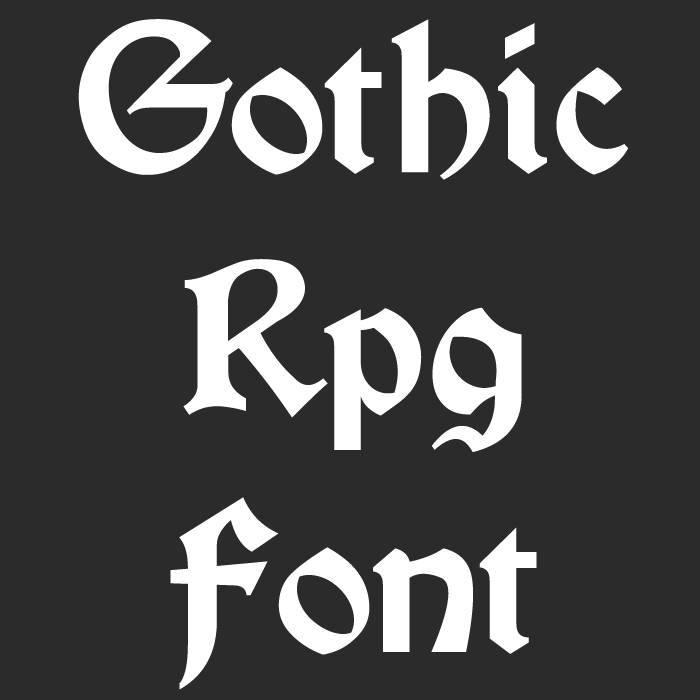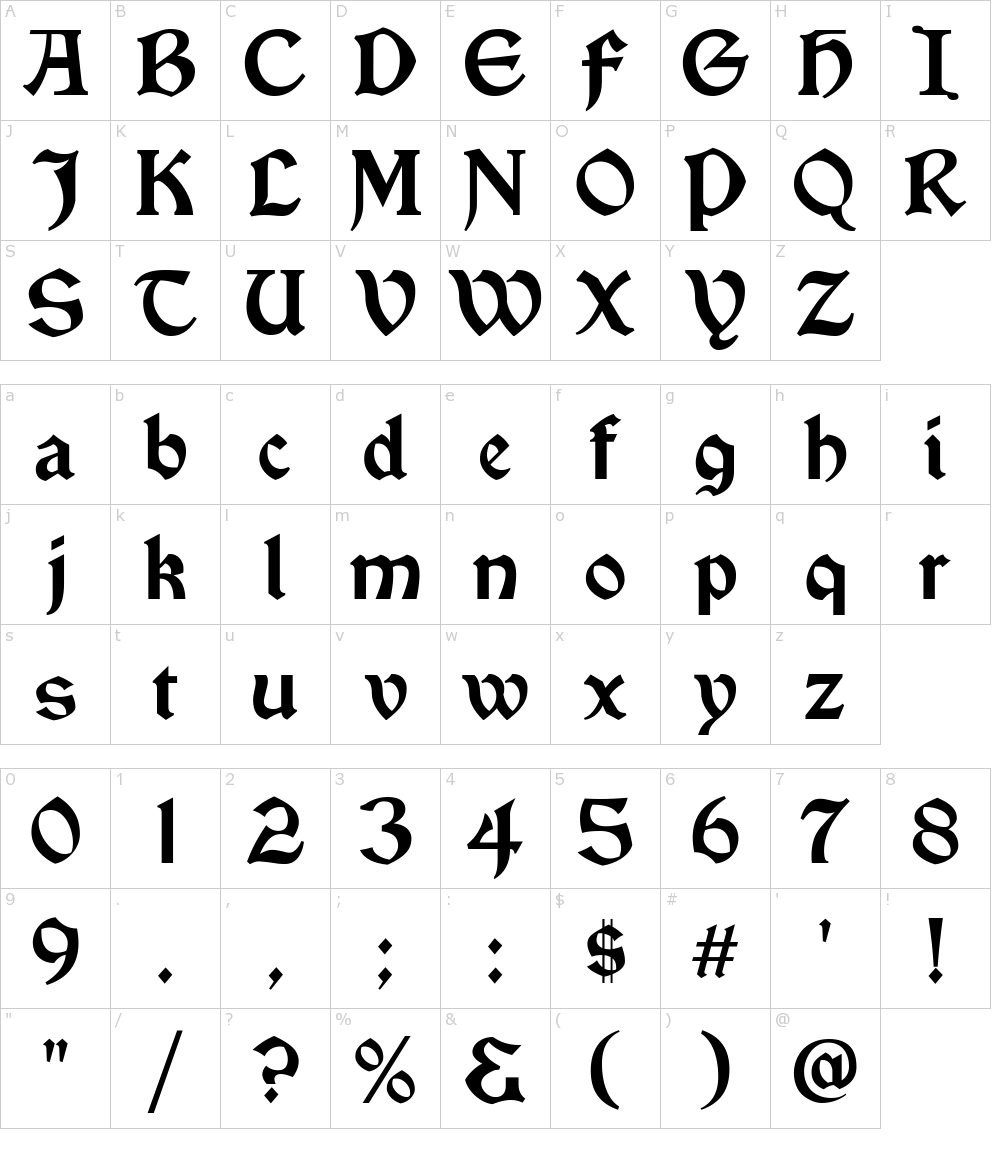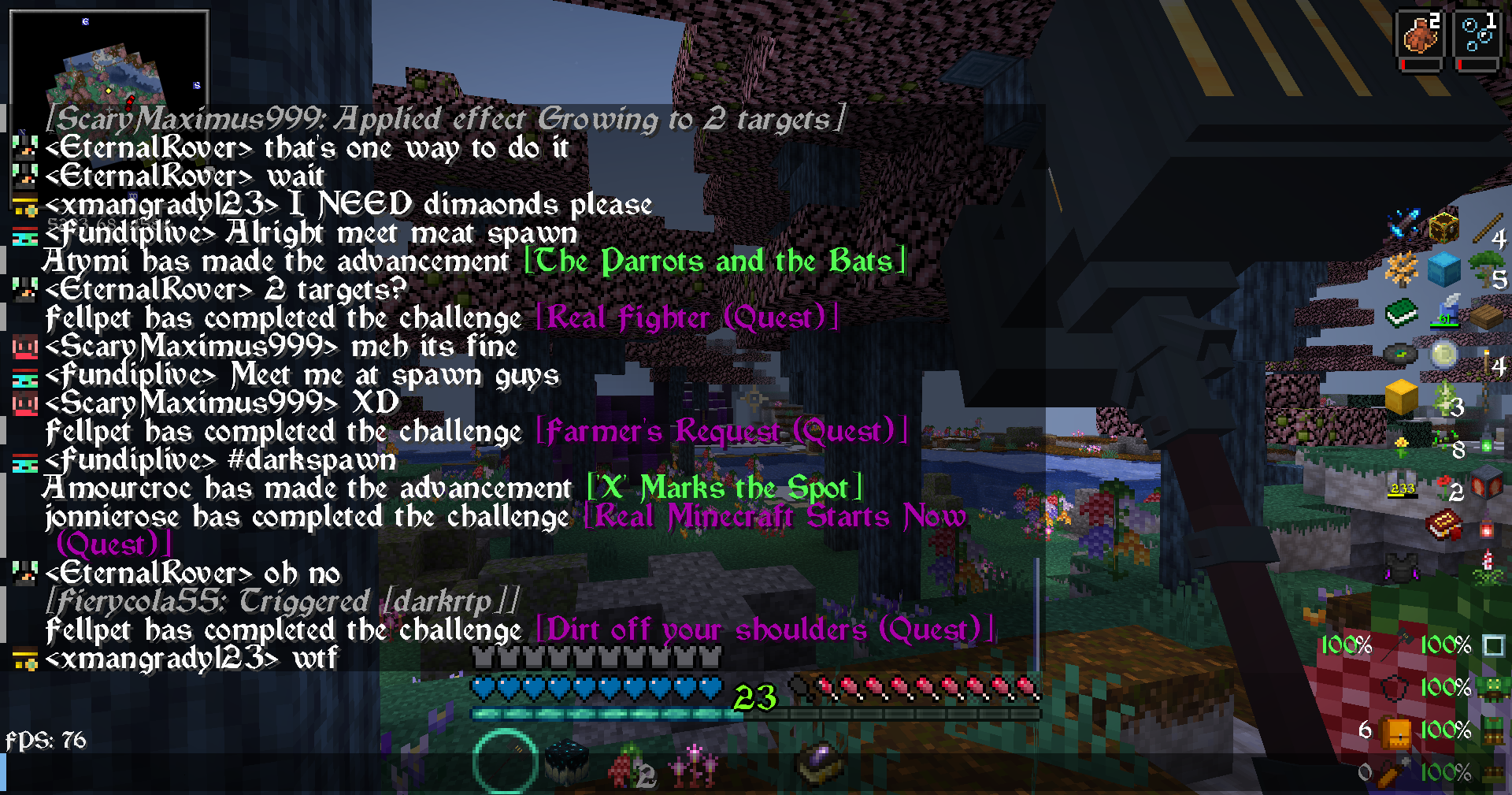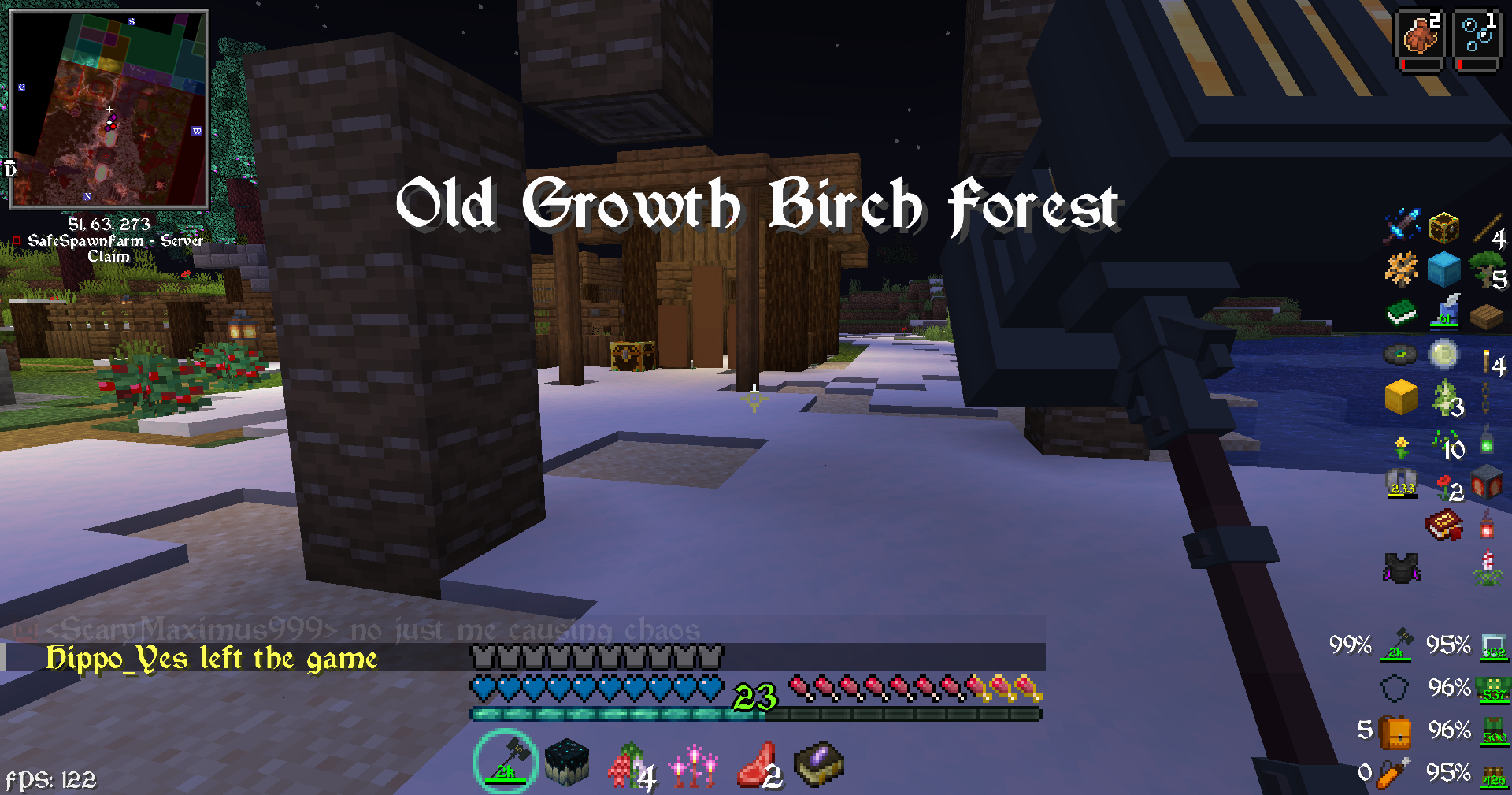
Gothic RPG Font для Minecraft: Погружение в средневековую атмосферу
Minecraft — это игра, где каждый может создать свой уникальный мир. Но что, если стандартные шрифты кажутся вам слишком обычными? Gothic RPG Font — это стильный готический шрифт, который превратит ваш интерфейс в нечто загадочное и средневековое. В этой статье разберём, как его установить, где использовать и почему он отлично подходит для RPG-режимов.
🔮 Что такое Gothic RPG Font?
Этот текстурный пакет заменяет стандартные шрифты Minecraft на готические, созданные в духе средневековья. Изначально он разрабатывался для модпака DarkRPG, но теперь доступен всем игрокам.
🔥 Особенности:
✔ Читаемость — несмотря на готический стиль, текст остаётся разборчивым.
✔ Атмосферность — идеально подходит для RPG-серверов и хардкорных выживаний.
🏰 Где использовать Gothic RPG Font?
Этот шрифт отлично сочетается с:
✅ RPG-модами (например, DarkRPG или Medieval MC).
✅ Серверами в стиле фэнтези или хоррора.
✅ Картами с сюжетом, где важна атмосфера.
Если вы играете на сервере с друзьями, такой шрифт добавит глубины вашему приключению.
🏁 Заключение
Gothic RPG Font — это отличный способ разнообразить Minecraft, добавив в него нотку средневековья. Простая установка, читаемый стиль и атмосферность делают его отличным выбором для любителей RPG и тёмных приключений.